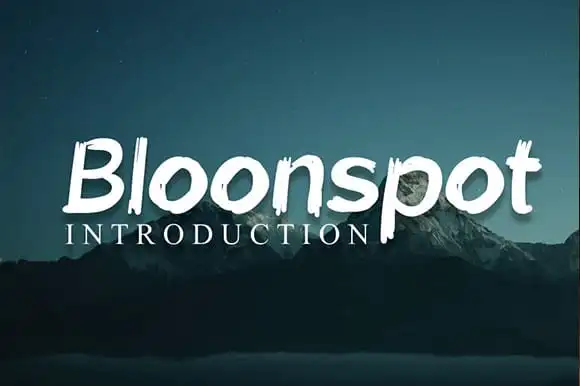
Bloonspot Displays Font – Download Grátis
A Bloonspot Displays Font é uma elegante escolha para designers que desejam dar um toque sofisticado a seus projetos. Perfeita tanto para aplicações publicitárias quanto para design editorial, essa fonte serif oferece texturas detalhadas e linhas suaves, tornando-a adequada para uma variedade de usos. Suas formas redondas e suas linhas retas são perfeitamente adaptáveis a ambientes que necessitam de texto de alta qualidade, seja em wall displays ou embalagens de produto. A Bloonspot Displays é um recurso valioso para designers apaixonados por criar estilos que combinam elegância com funcionalidade, ideal para aplicar seu próprio toque pessoal em uma gama de materiais e aplicações, desde as embalagens até os posts no Instagram, das cartas de aniversário às campanhas publicitárias. Esta fonte é certamente um recurso essencial para qualquer biblioteca de recursos gráficos.